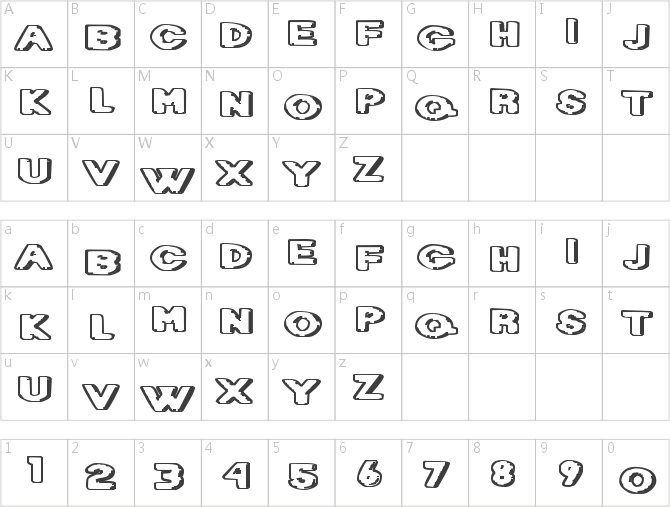
字體名稱: Diet Dr
Diet Dr. Creep
Diet Dr. Creep字體字庫(kù)是一款讓人賞心悅目、百看不厭的英文字體,適合各類廣告和產(chǎn)品包裝設(shè)計(jì)應(yīng)用,字體大小0.04MB,格式為ttf字體,上傳用戶是小猴子1003,作者/版權(quán)方為未知